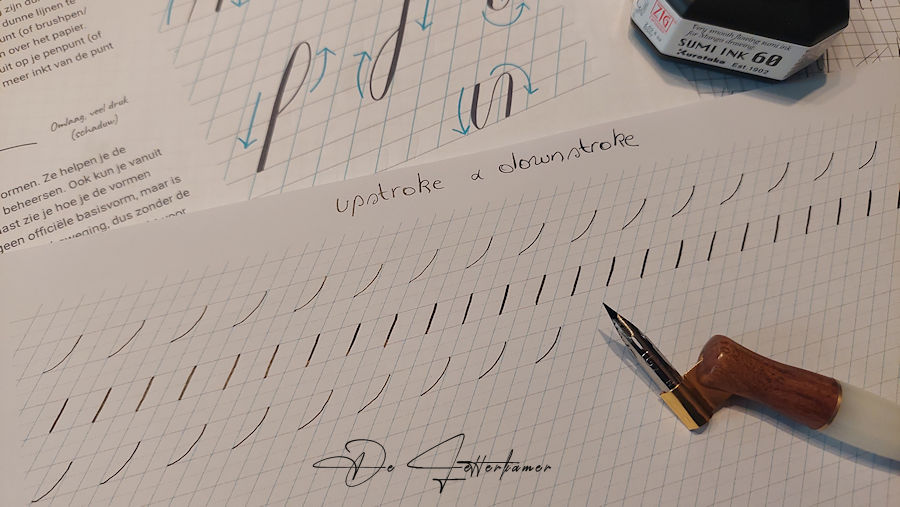
Zo, mijn 1ste mail vandaag was: “jouw bestelling wordt vandaag geleverd”: dé inkt “Kuretake Sumi Ink 60” dacht ik bij mezelf. Dat was deze ochtend.
Ik was benieuwd hoe deze ging schrijven, ik merkte meteen dat het iets fijnere inkt was dan mijn voorgaande. Het schrijven ging veel vlotter, en de inkt bleef ook niet plakken aan de nib. Ik was begonnen met upstroke en downstroke, de basisvormen. Heel eenvoudig.
Ik bewaar mijn oefenbladen zodat ik nog eens kan terug kijken naar mijn evolutie. Ik vind het eigenlijk best wel leuk om te doen.
Deze basisvormen zorgen er voor dat we letters kunnen vormen:
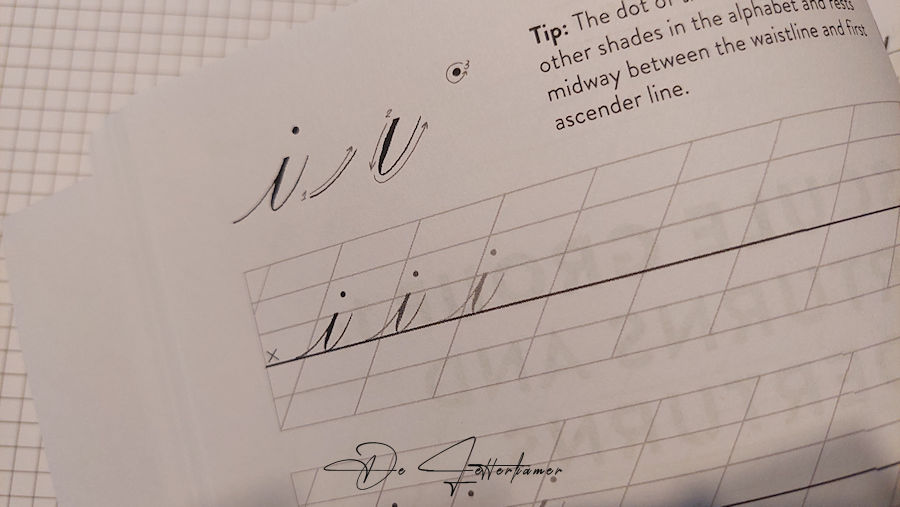
Daar bovenaan wordt de letter “i” gevormd met 2 basisvormen. Ze werken wel met andere oefenbladen, ik gebruik die dat ik voor me heb liggen.
Ik kon me niet inhouden, ik heb deze letter geprobeerd. En dat ging redelijk en met de oblique penhouder(?), ook geen probleem, dat ging ook heel vlot. De volgende keer oefen ik verder met de 8 basisvormen. Tot het goed in mijn vingers zit.